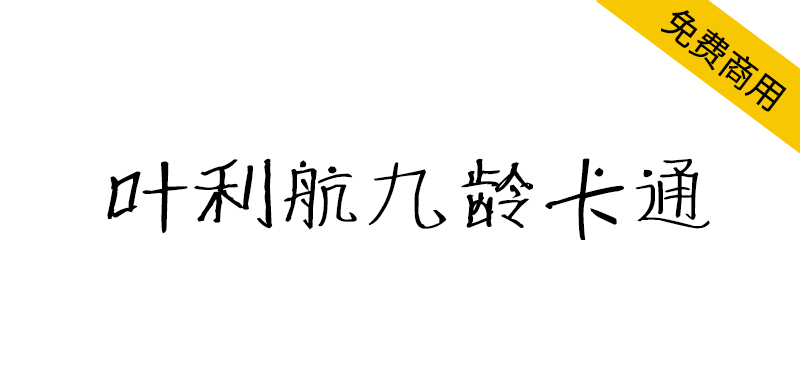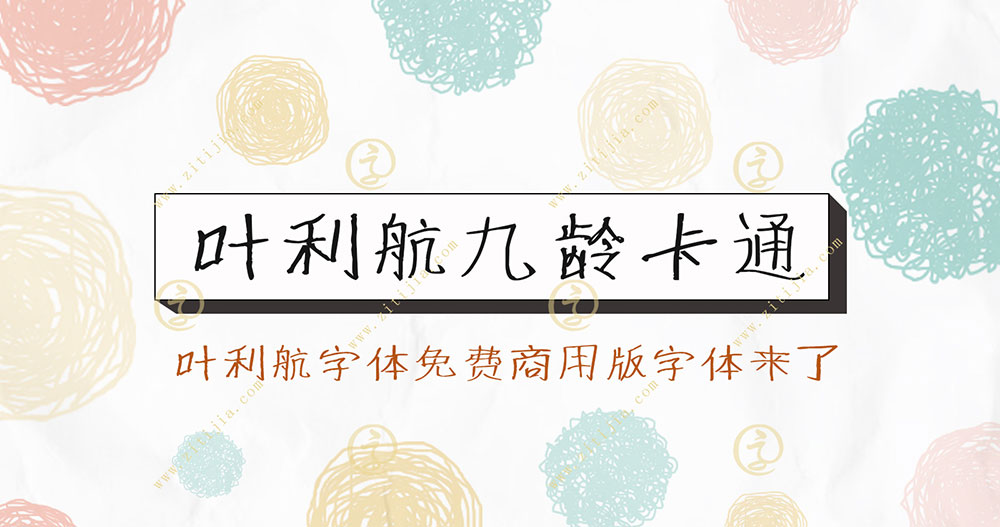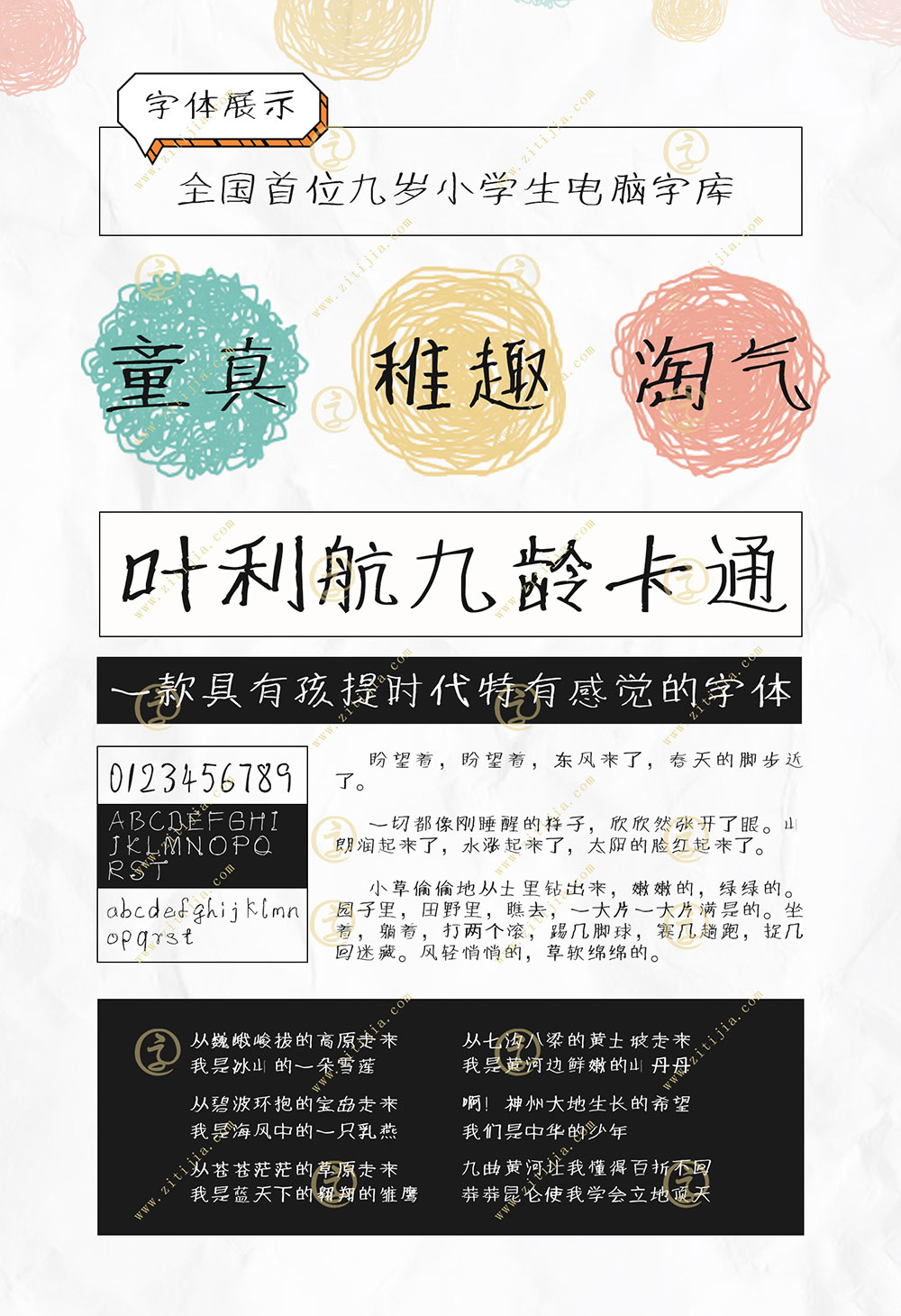
【叶利航九龄卡通】可爱稚嫩的儿童卡通风格手写字体
九岁孩子写的字,到底能有多特别?这款由四年级小学生叶利航创作的稚嫩手写字体,完美复刻了儿童天真烂漫的笔触。每个歪歪扭扭的笔画都散发着独特的童趣魅力,正是设计师们苦苦寻觅的卡通风格字体。更令人惊喜的是,它完全免费商用!无论是儿童海报、品牌包装还是文创设计,都能立即为作品注入纯真活力。想知道如何把这份童真融入你的创意项目吗?
【叶利航九龄卡通】可爱稚嫩的儿童卡通风格手写字体
叶利航九龄卡通这款字体是在叶利航九岁(四年级)书写的字体,幼稚的笔画中透露出一种儿童风格的可爱和稚嫩,这种具有卡通风格,不太规整的笔画正是有一种其他人书写不出的风格,叶根友认为,字体创意讲究一种风格是否独特,是不是有与众不同的汉字体裁,书法家写出来的字体和小孩子写的是两种不同韵味的汉字字体,这样的字体用于一些儿童海报设计,卡通可爱的载体应用都是非常贴切主题的。
【叶利航九龄卡通】可爱稚嫩的儿童卡通风格手写字体